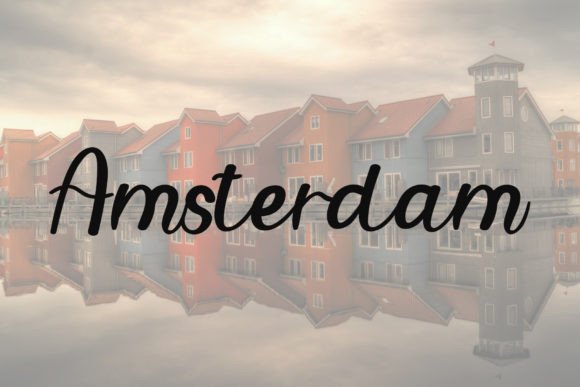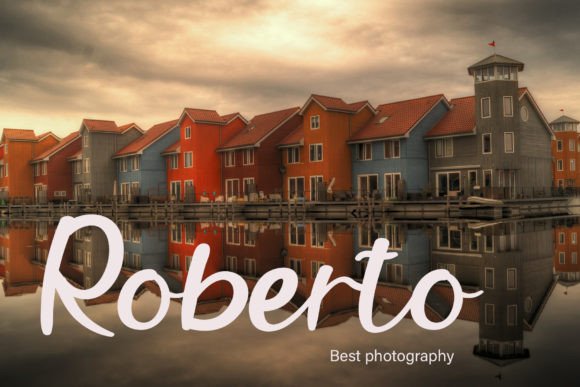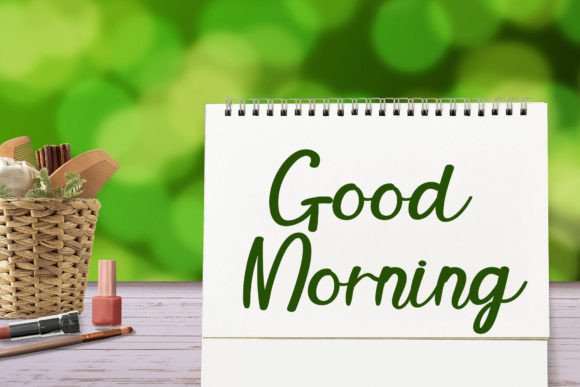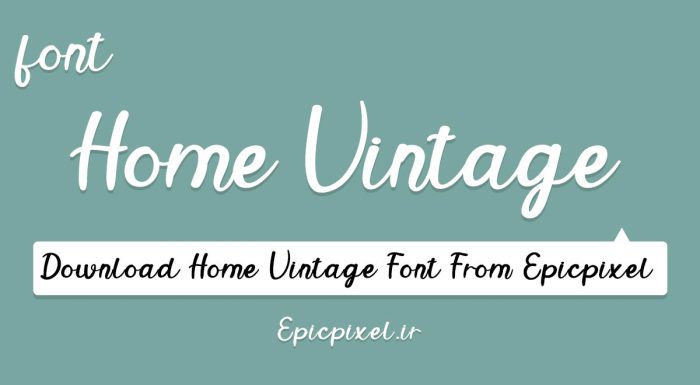
فونت Home Vintage انگلیسی
| ⭐ توضیحات | فونت هوم وینتیج را معرفی میکنیم، خطی نوستالژیک و جذاب و حروف دستنویسی که جوهر خانههای قدیمی و خاطرات دنج را تداعی میکند. این فونت با منحنی های ظریف و حروف الهام گرفته شده از یکپارچهسازی با سیستمعامل، حس گرما و شخصیت را به طرح های شما می بخشد.
فونت Home Vintage که برای برندسازی با مضمون قدیمی، تابلوهای نوستالژیک و پروژه های دکور خانه ایده آل است، حس جذابیت و نوستالژی بی انتها را به ارمغان می آورد و فضایی دلپذیر و دعوت کننده برای مخاطبان شما ایجاد می کند. |